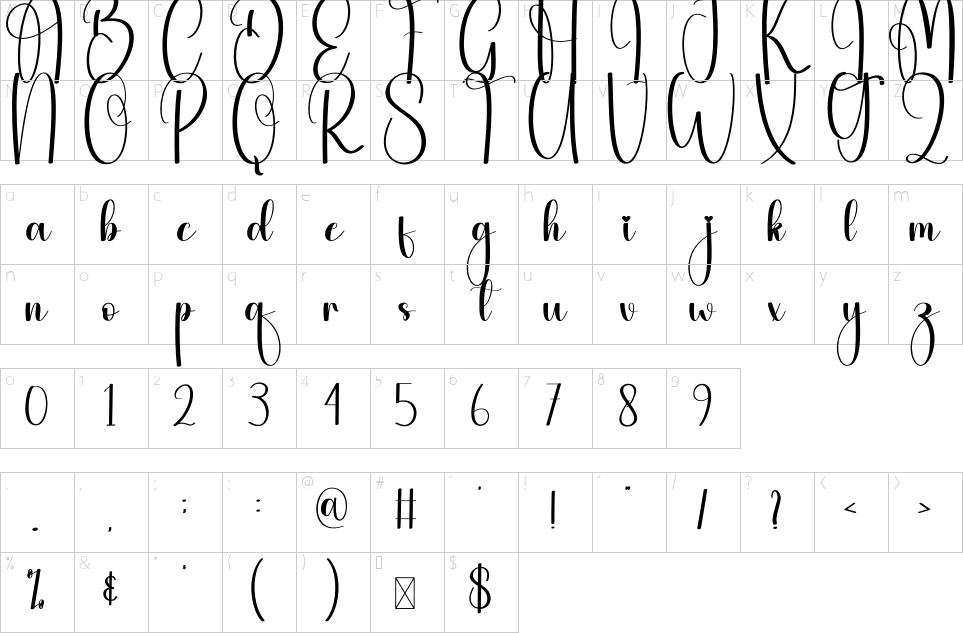
A Maddison Font é uma fonte livre de alta qualidade, projetada por um criador desconhecido e já baixada 454 vezes. Suavemente elegante, essa fonte é perfeita para designers que buscam um visual moderno e sofisticado. Suporte a Windows e Mac, a Maddison é uma escolha ótima para aqueles que buscam gráficos limpos e profissionais. Se você está procurando por um recurso de fonte que seja de alto padrão e disponível para uso gratuito, a Maddison é uma excelente escolha. Adquira-a agora e dê um novo tom para suas criações.